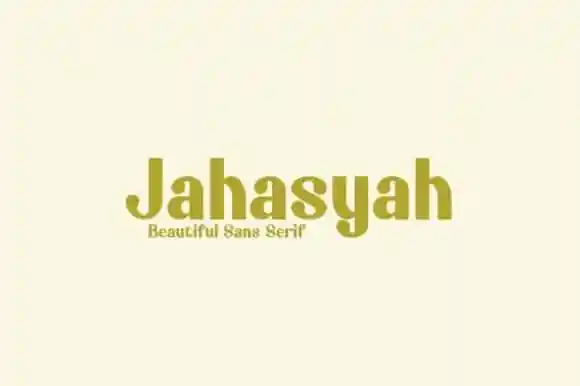
Introduzimos Jahasyah Sans Serif Font – uma tipografia sans serif moderna e robusta com muitas ligaturas e alternativas. Esta font foi meticulosamente projetada para se tornar um favorito, prometendo transformar cada ideia criativa em seu melhor estado. Com suas linhas arredondadas e elegantes, Jahasyah é perfeito para quem busca uma personalidade única que ressoa com o mundo digital atual. Ideal tanto para textos de uso geral quanto para design gráfico avançado, essa fonte oferece a oportunidade de dar um toque único à sua arte digital. Descubra por si mesmo como ela pode enriquecer seu trabalho.